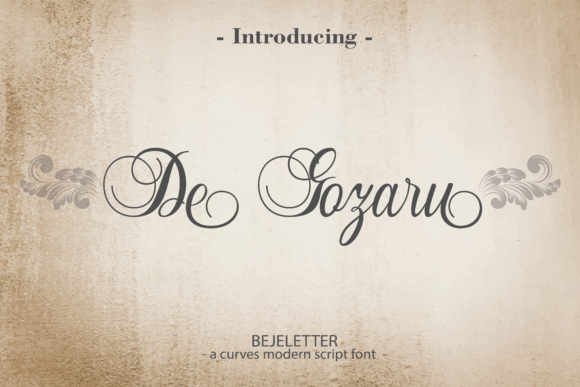
Де Гозару - это классический каллиграфический шрифт с красивой аркой.
Этот шрифт доступен в нескольких современных вихрях, которые могут сделать вашу работу элегантной, сладкой и совершенной.
Этот шрифт также имеет несколько альтернатив, которые могут позволить вам импровизировать с вашим письмом.